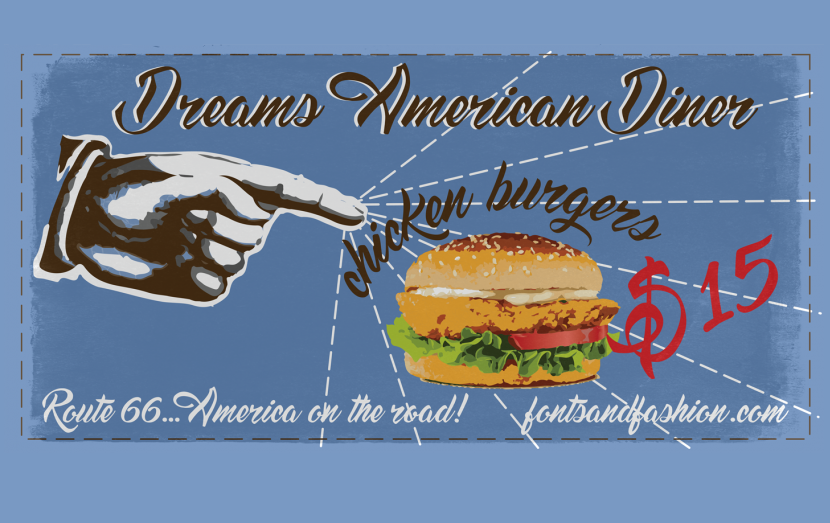
A nova fonte ‘Dreams American Diner Font’ trouxe à vida uma ideia que vem do pensamento culinário — a ideia de como os ingredientes podem se transformar em belas letras. Esta fonte foi inspirada no movimento artístico dos restaurantes da Route 66, onde as antigas placas de propaganda e os menus de restaurantes antigos ainda são visíveis, permitindo-nos viajar no tempo. É uma combinação delicada e elegante que captura a essência do entretenimento gastronômico americano à escala mundial. O design é inspirado em influências culinárias como tex-mex, barbecue e hamburgueres, tudo isso embutido em um letrito delicado e sofisticado. A fonte ‘Dreams American Diner Font’ evoca os anos 50 dos Estados Unidos, quando a propaganda era parte integrante de qualquer estabelecimento de alimentação. E embora o design seja moderno e up-to-date, ele ainda mantém uma atmosfera nostálgica que remete aos tempos passados. É uma fonte perfeita para menus ou posters, oferecendo ao mesmo tempo um toque sofisticado e autêntico do universo culinário americano. Sem dúvida, ‘Dreams American Diner Font’ é a escolha ideal para quem deseja capturar a essência de uma experiência gastronômica através da tipografia.